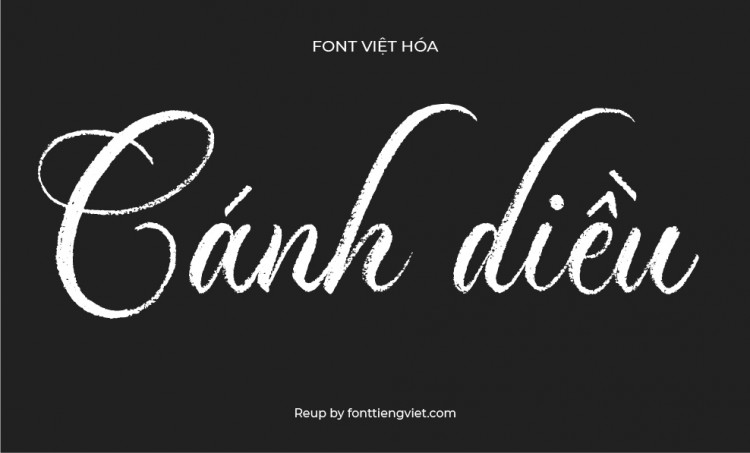
Font việt hóa SVN Dayland
Giới thiệu về Font việt hóa SVN Dayland
Trong thế giới đồ họa hiện đại, việc tìm kiếm một Font Miễn Phí chất lượng luôn là ưu tiên hàng đầu của các nhà thiết kế. Font việt hóa SVN Dayland là một bộ phông chữ độc đáo, mang phong cách mạnh mẽ nhưng không kém phần uyển chuyển. Được tinh chỉnh kỹ lưỡng để phù hợp với bảng mã tiếng Việt, bộ font này giúp người dùng tránh được các lỗi hiển thị dấu phổ biến, từ đó tạo nên những tác phẩm chuyên nghiệp và thẩm mỹ hơn.
Ưu điểm nổi bật của Font việt hóa SVN Dayland
Phong cách thiết kế sáng tạo
SVN Dayland sở hữu những đường nét phóng khoáng, rất phù hợp cho các dự án thiết kế tiêu đề, bìa sách, poster hoặc các ấn phẩm quảng cáo cần sự đột phá. Sự kết hợp giữa nét dày và mảnh tạo nên nhịp điệu thị giác ấn tượng, giúp thông điệp của bạn dễ dàng thu hút sự chú ý của người xem ngay từ cái nhìn đầu tiên.
Khả năng ứng dụng đa dạng
Không chỉ dừng lại ở các thiết kế hiện đại, Font việt hóa SVN Dayland còn rất linh hoạt khi áp dụng vào các chủ đề mang tính hoài cổ hoặc nghệ thuật chữ viết tay. Bạn có thể sử dụng bộ chữ này trên các phần mềm đồ họa phổ biến như Photoshop, Illustrator hay cả trong các ứng dụng văn phòng cơ bản để làm mới nội dung trình bày.
Kết luận về bộ font chữ đẹp